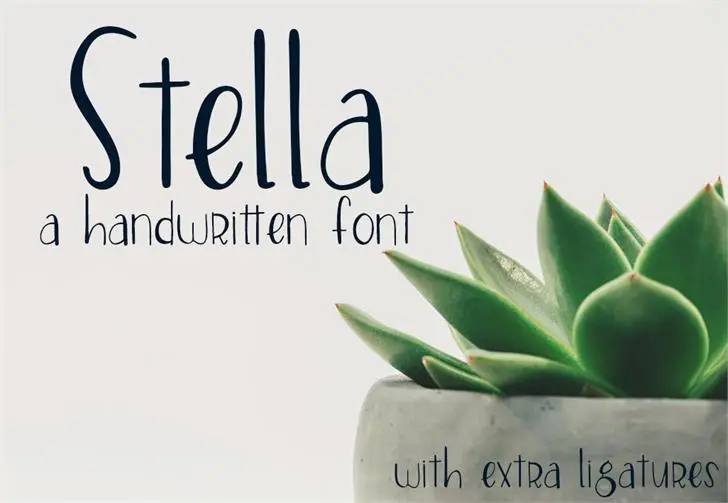
Stella Font
A Stella Font é uma deliciosa mão-dura que traz para você uma escrita delicada e elegante. Ideal para aqueles que buscam expressar sutileza em suas criações digitais, essa fonte é perfeita para adicionar um toque especial a qualquer projeto gráfico. Se você apreciou a Stella Font e gostou do estilo, consideramos um pequeno esforço de sua parte fazer uma doação de $1. Essa contribuição não apenas ajudará nós a dedicar mais tempo ao design da fonte, mas também nos permitirá continuar criando novas maneiras únicas para você explorar em seu próximo projeto. Estamos extremamente gratos por todo o apoio que recebemos e esperamos poder retribuí-lo com cada nova versão de nossa Stella Font.